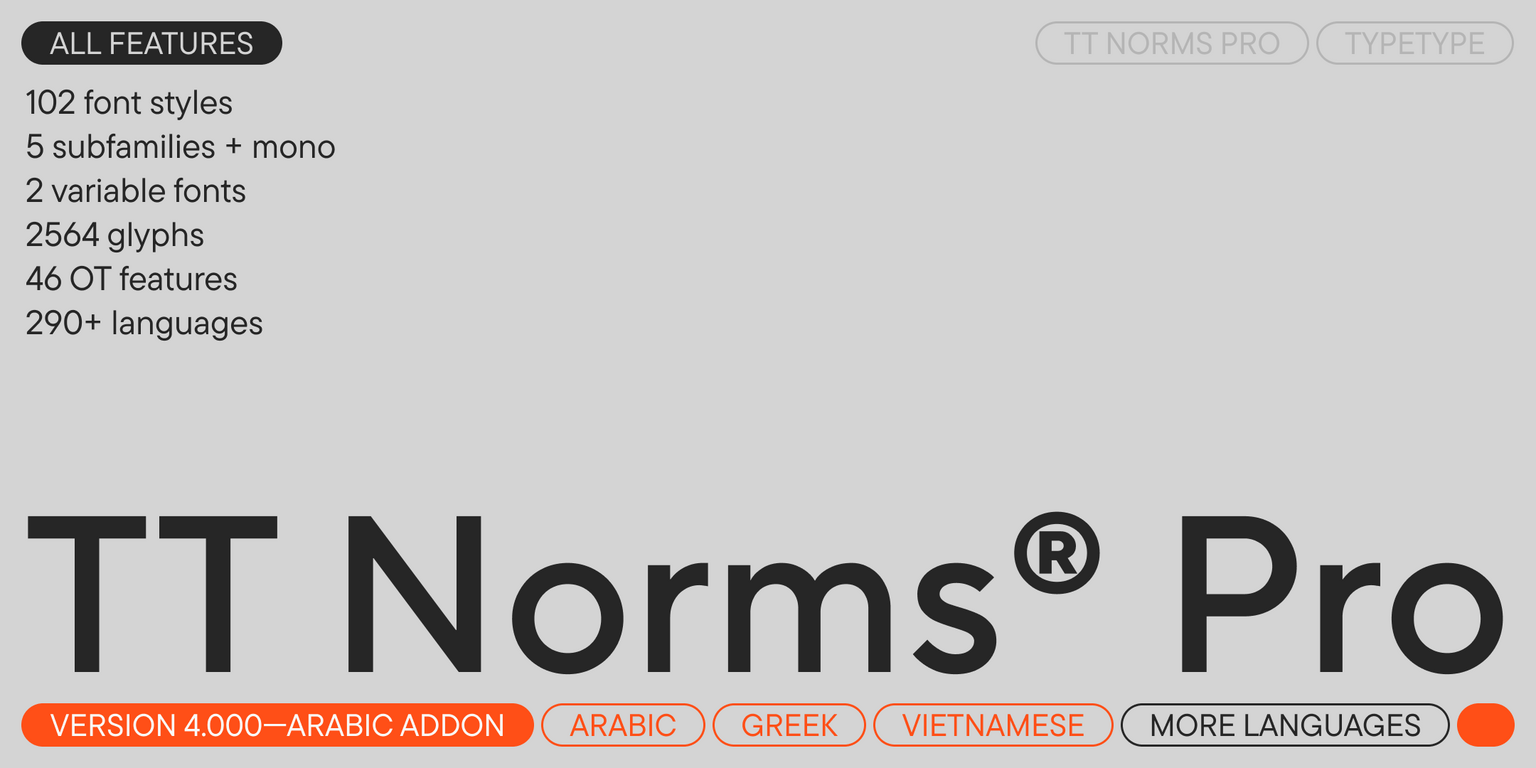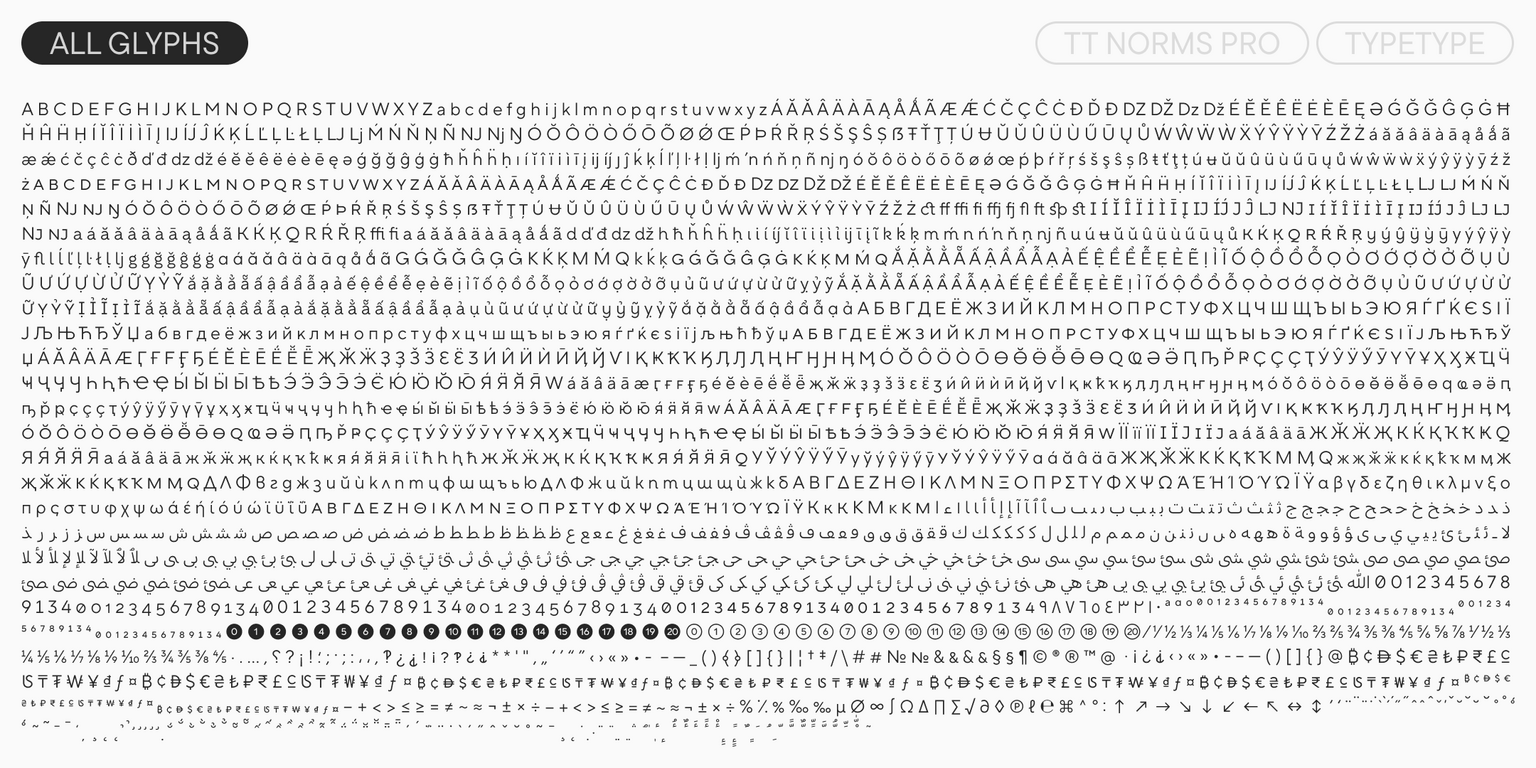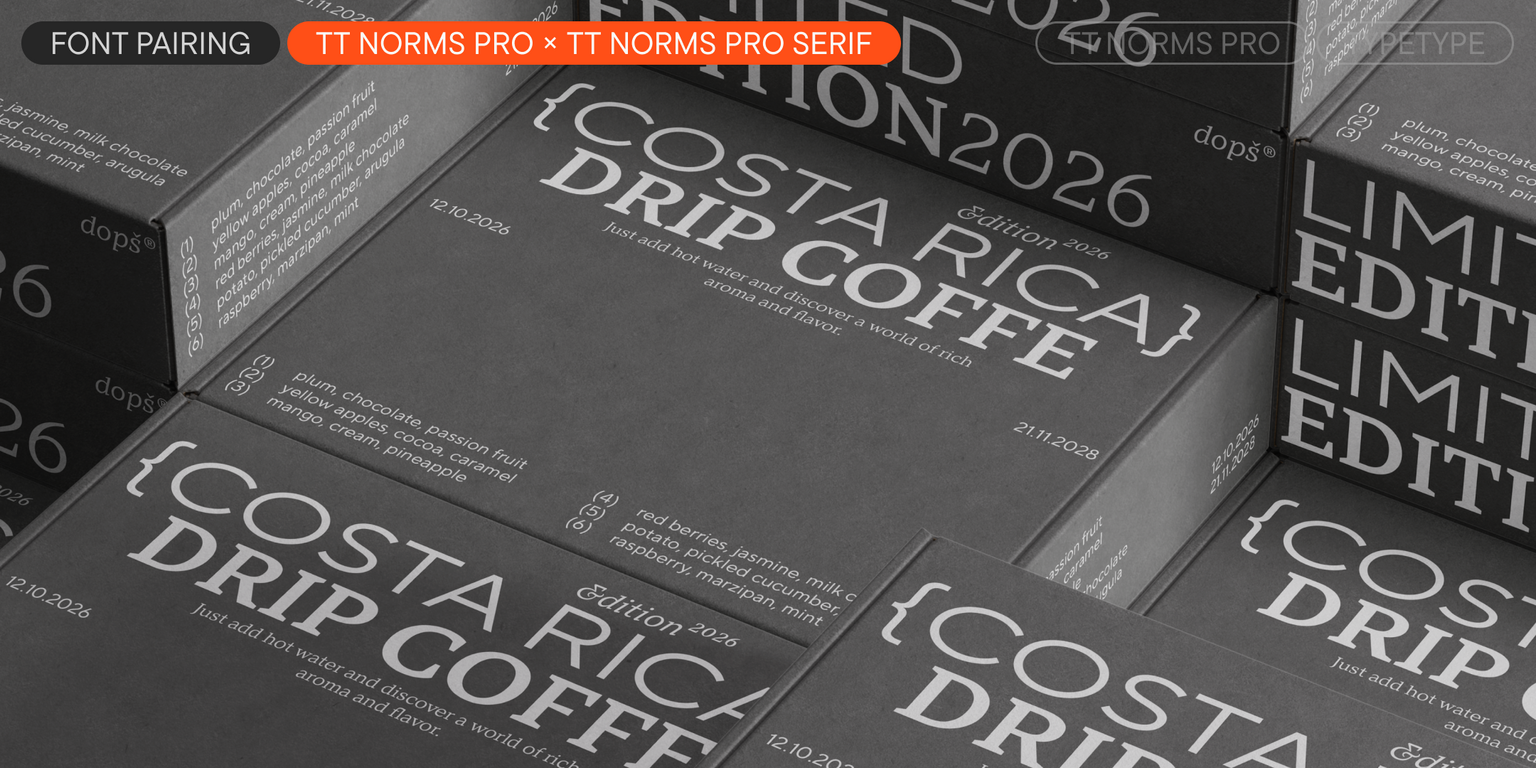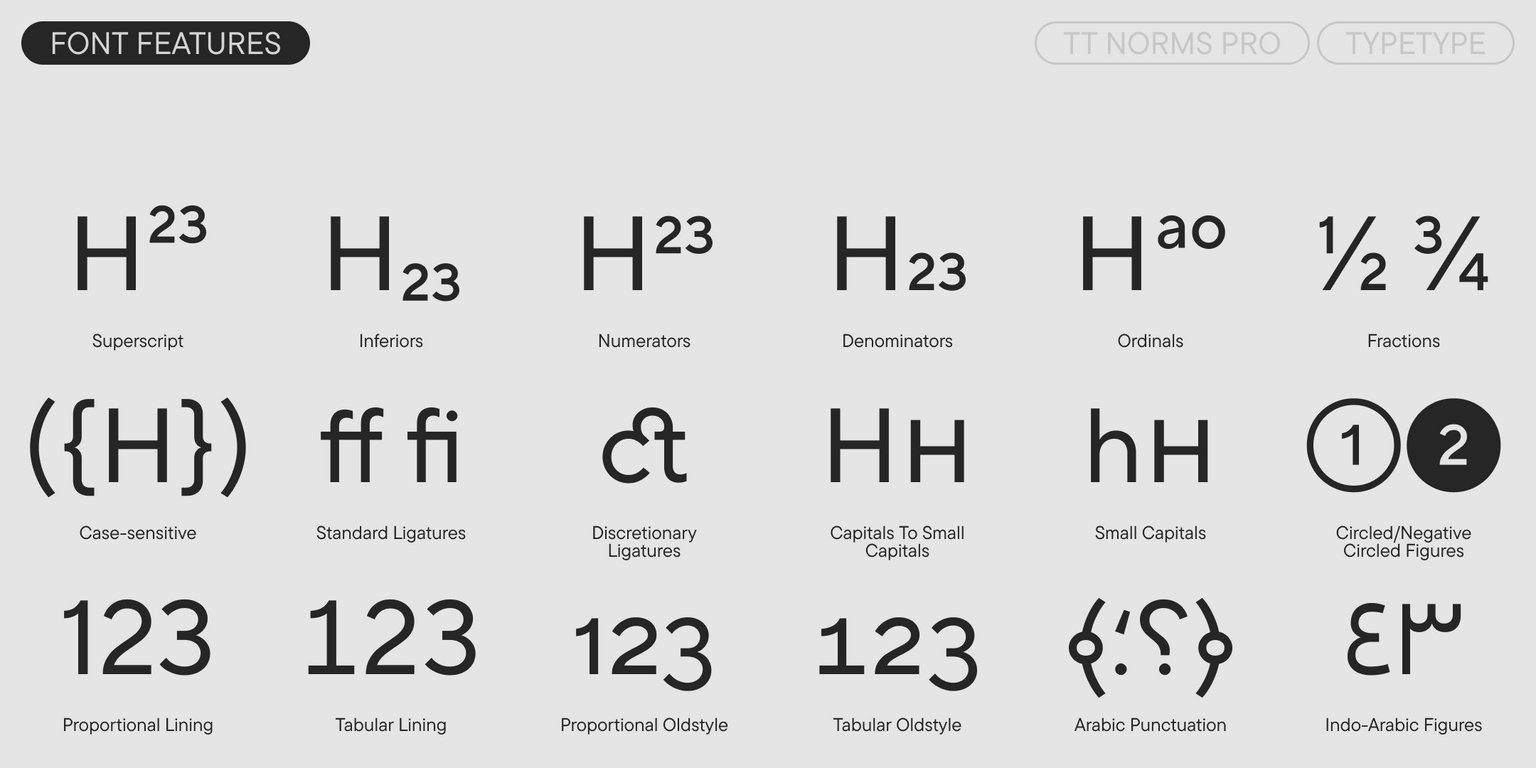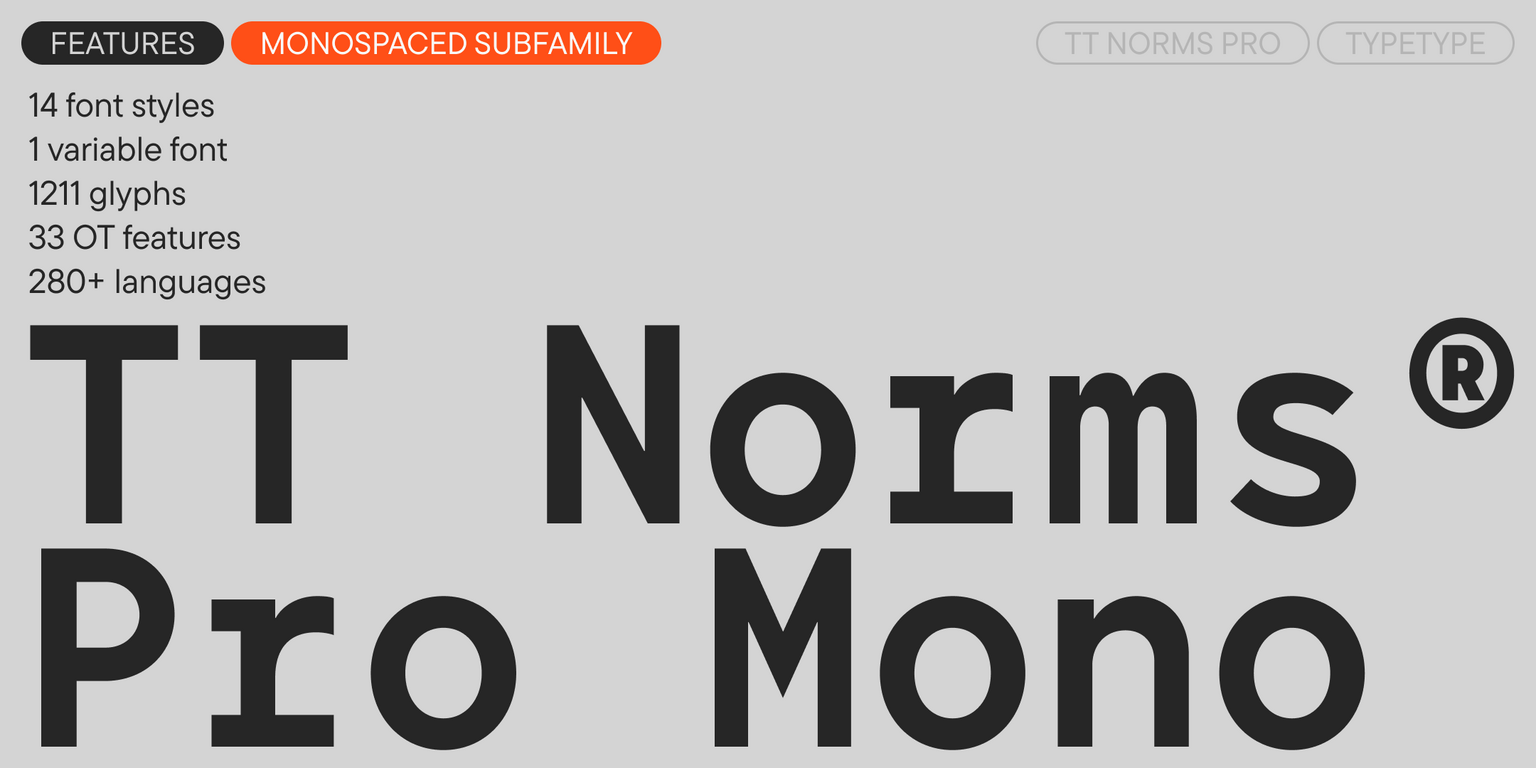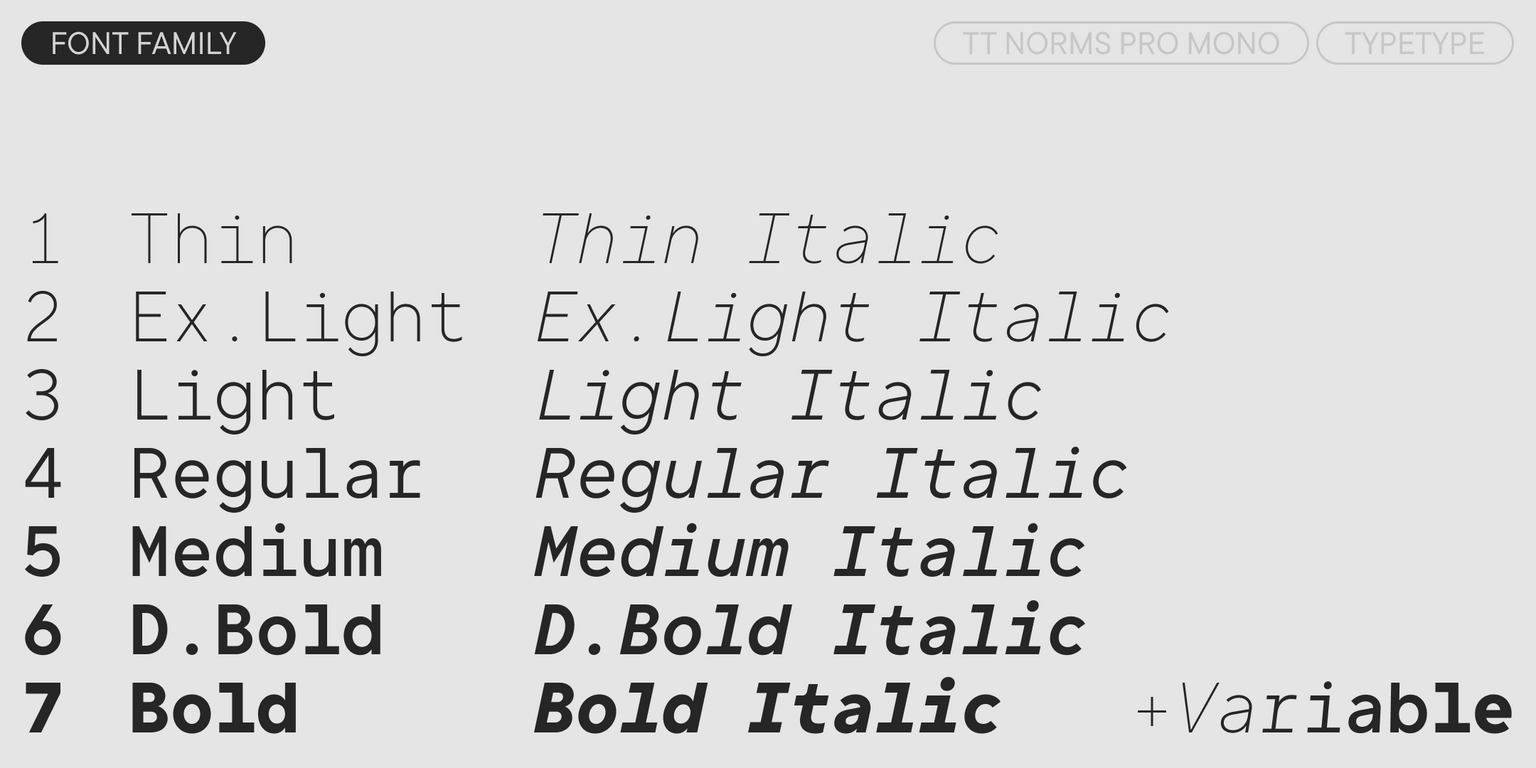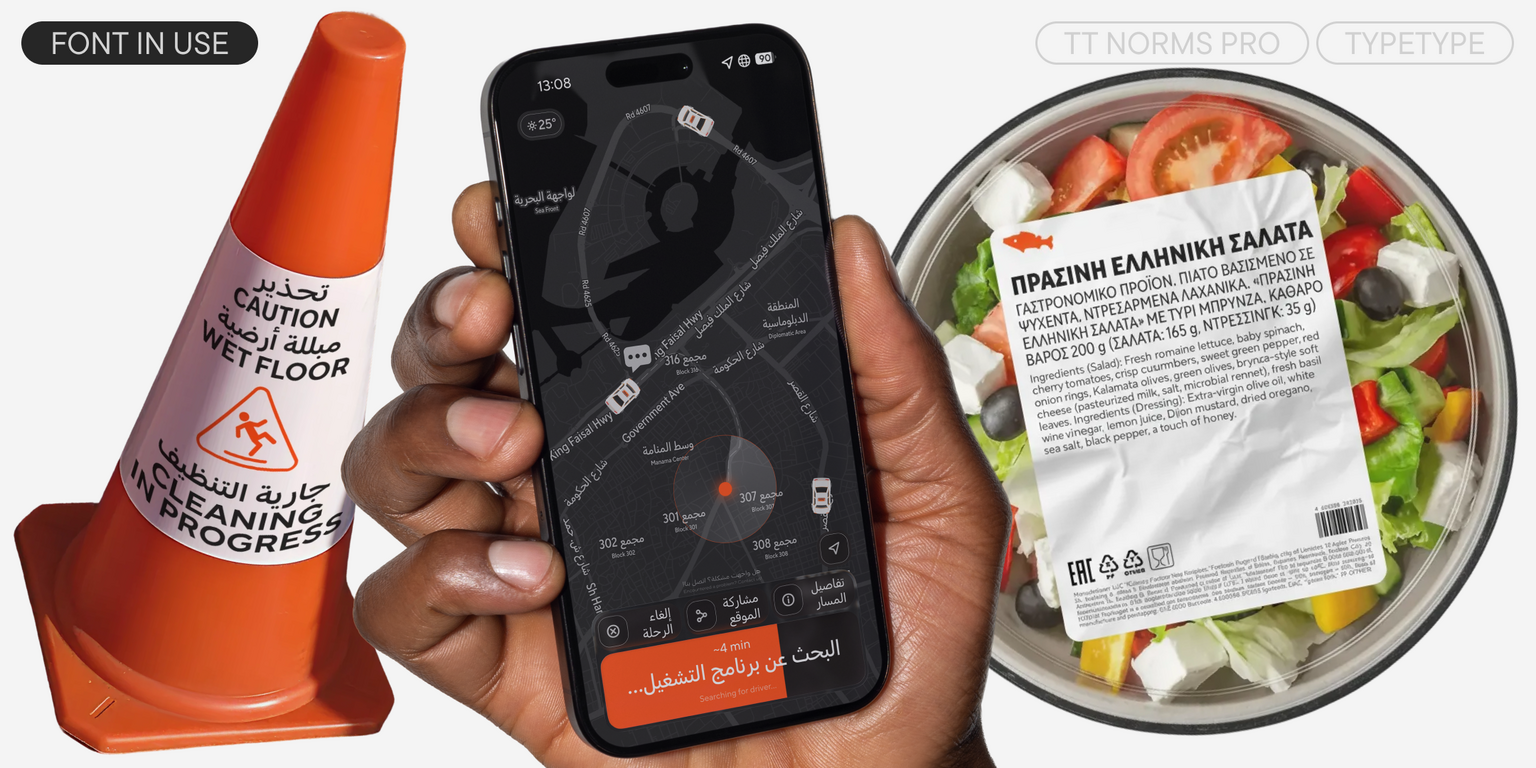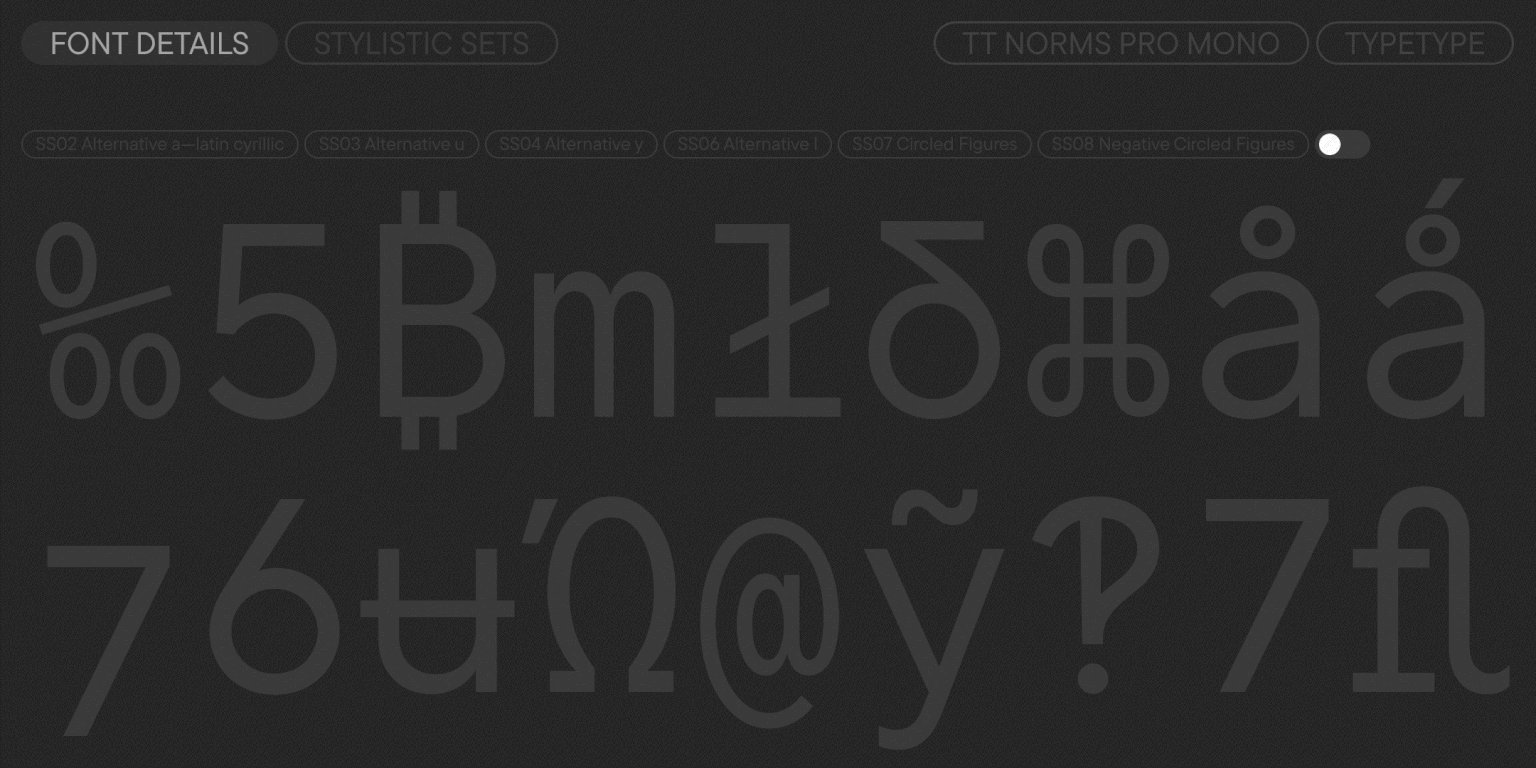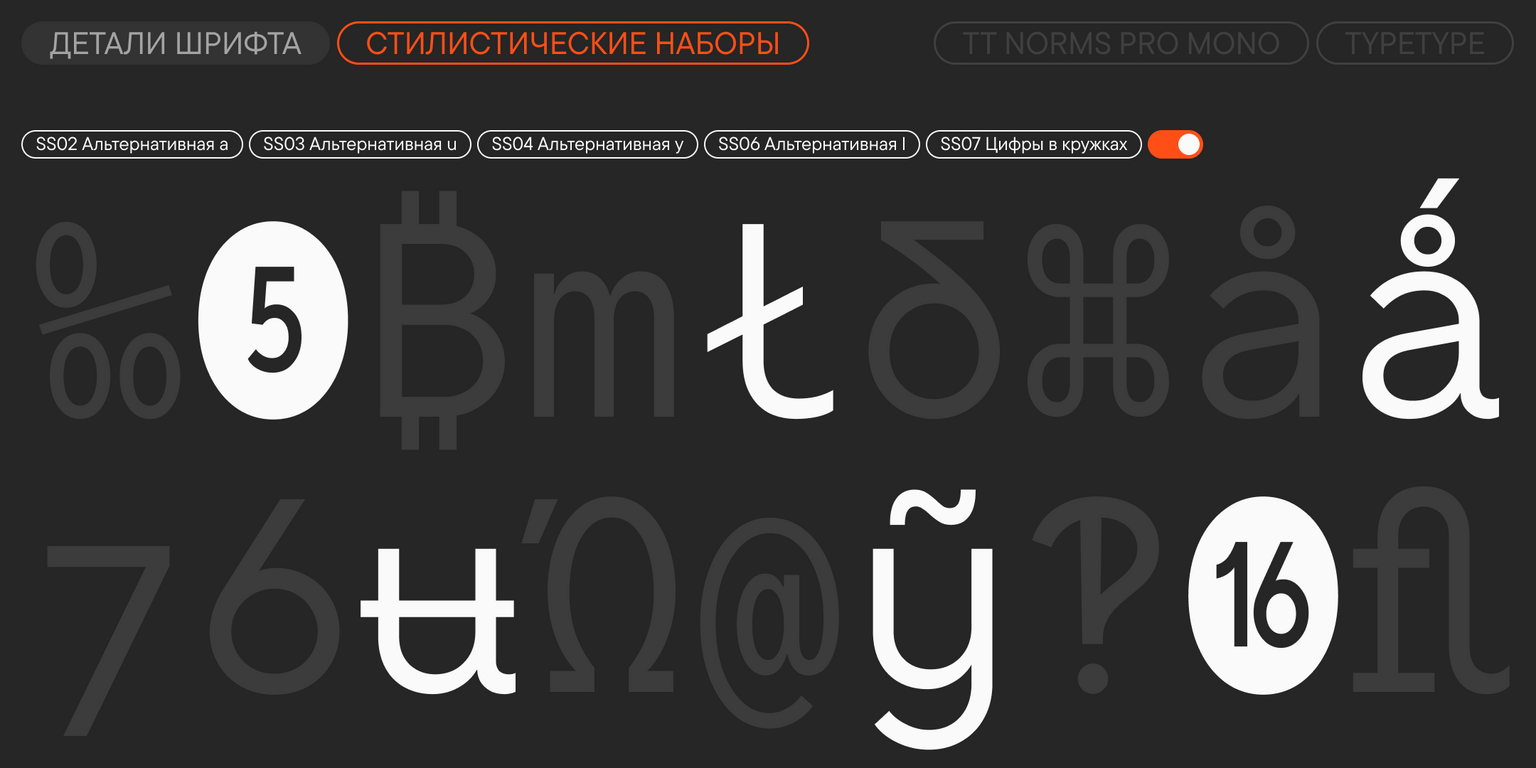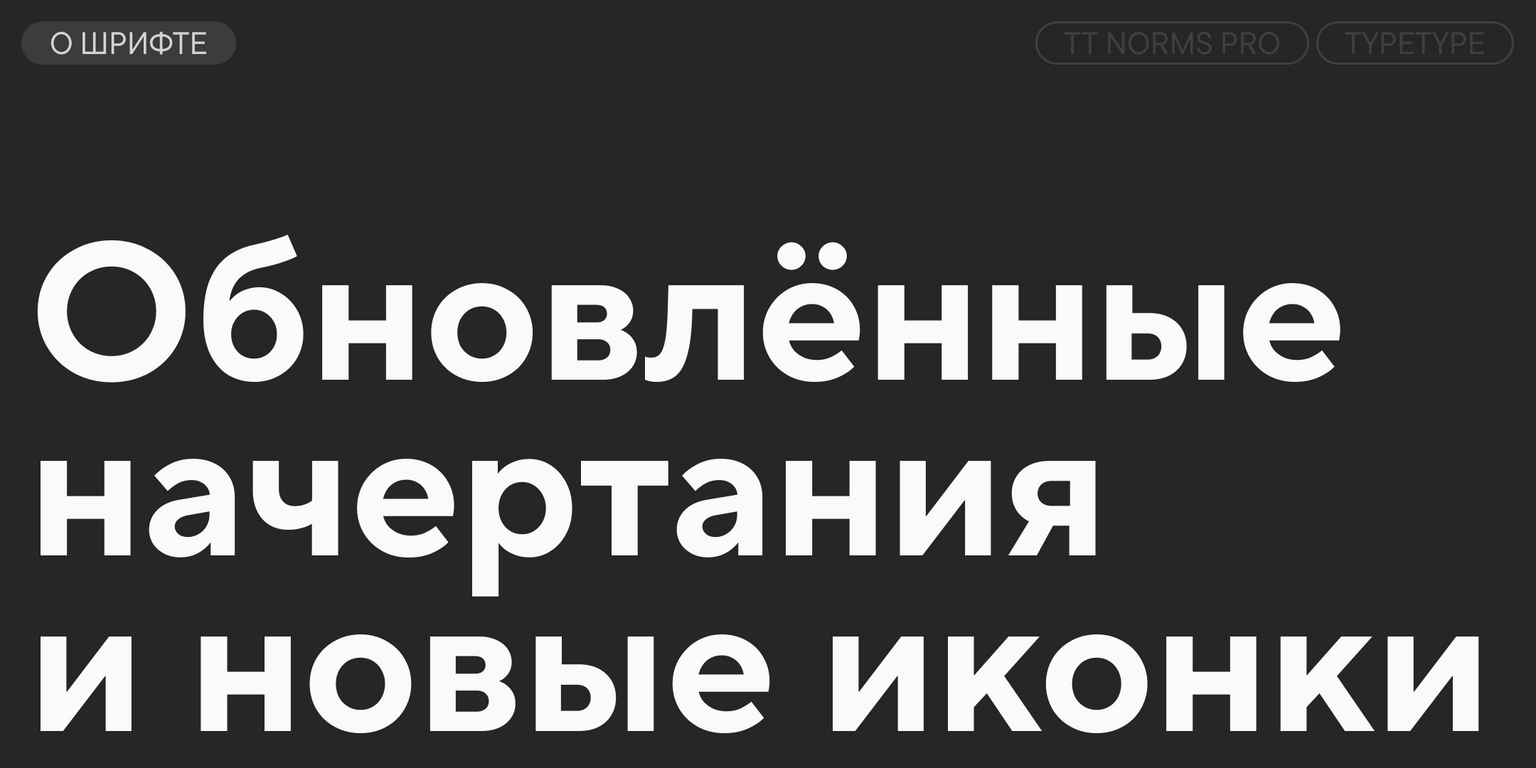
TT Norms® Pro
TT Norms® Pro — TT Нормс Про
TT Norms® Pro — функциональный геометрический гротеск для эстетичных решений. Бестселлер студии, который выбирают известные мировые бренды.
TT Norms® Pro — главный геометрический гротеск от студии TypeType